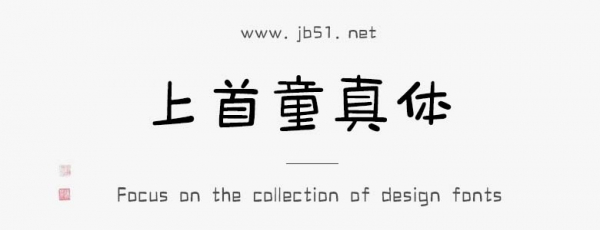
上首童真體是由上首造字字庫(kù)出品的字體,字體筆觸適中,字形端正,趣味十足,具有很好的視覺(jué)感,適合應(yīng)用于藝術(shù)設(shè)計(jì)、平面宣傳設(shè)計(jì)、網(wǎng)頁(yè)設(shè)計(jì),書(shū)法字帖等領(lǐng)域,需要的朋友可以前來(lái)本站下載。